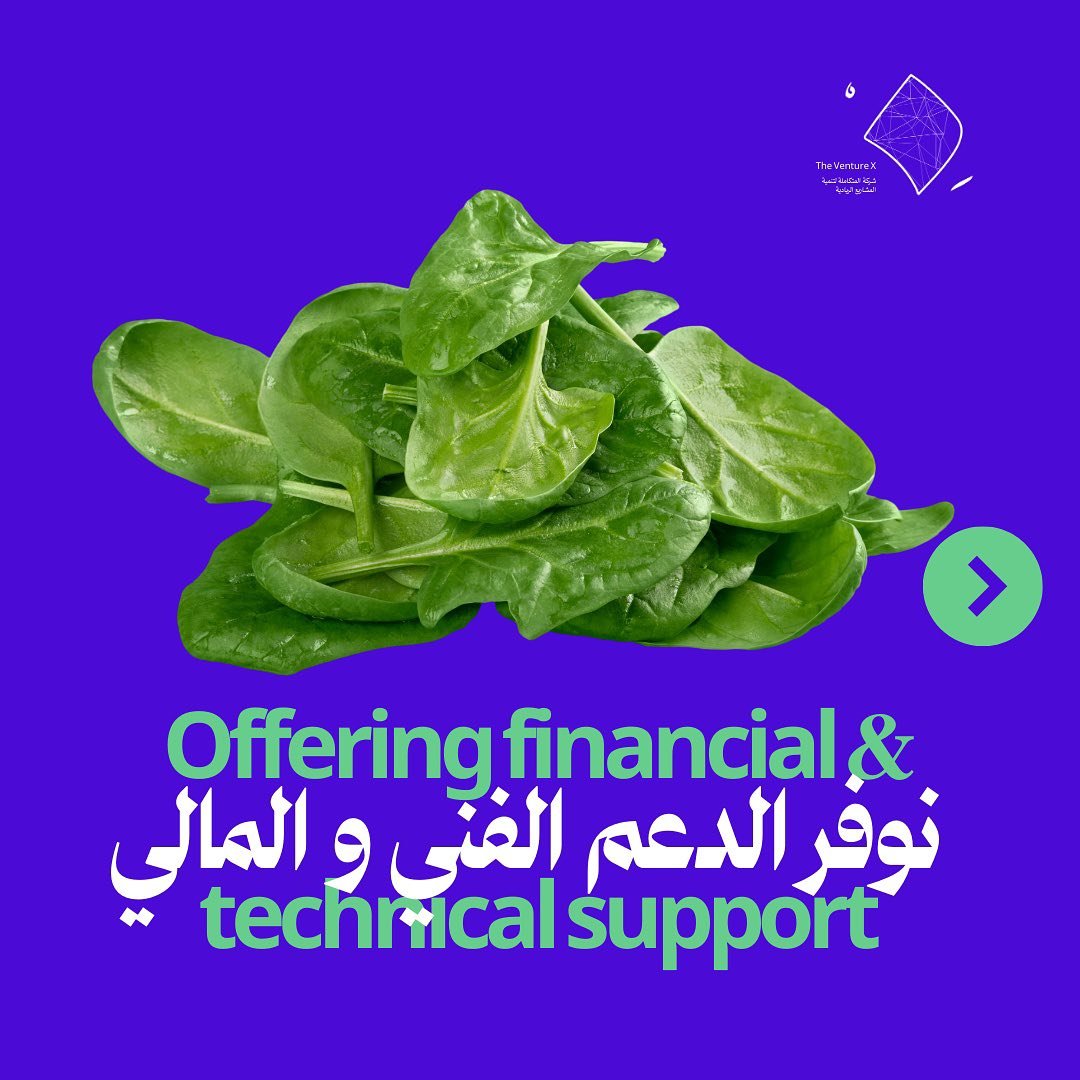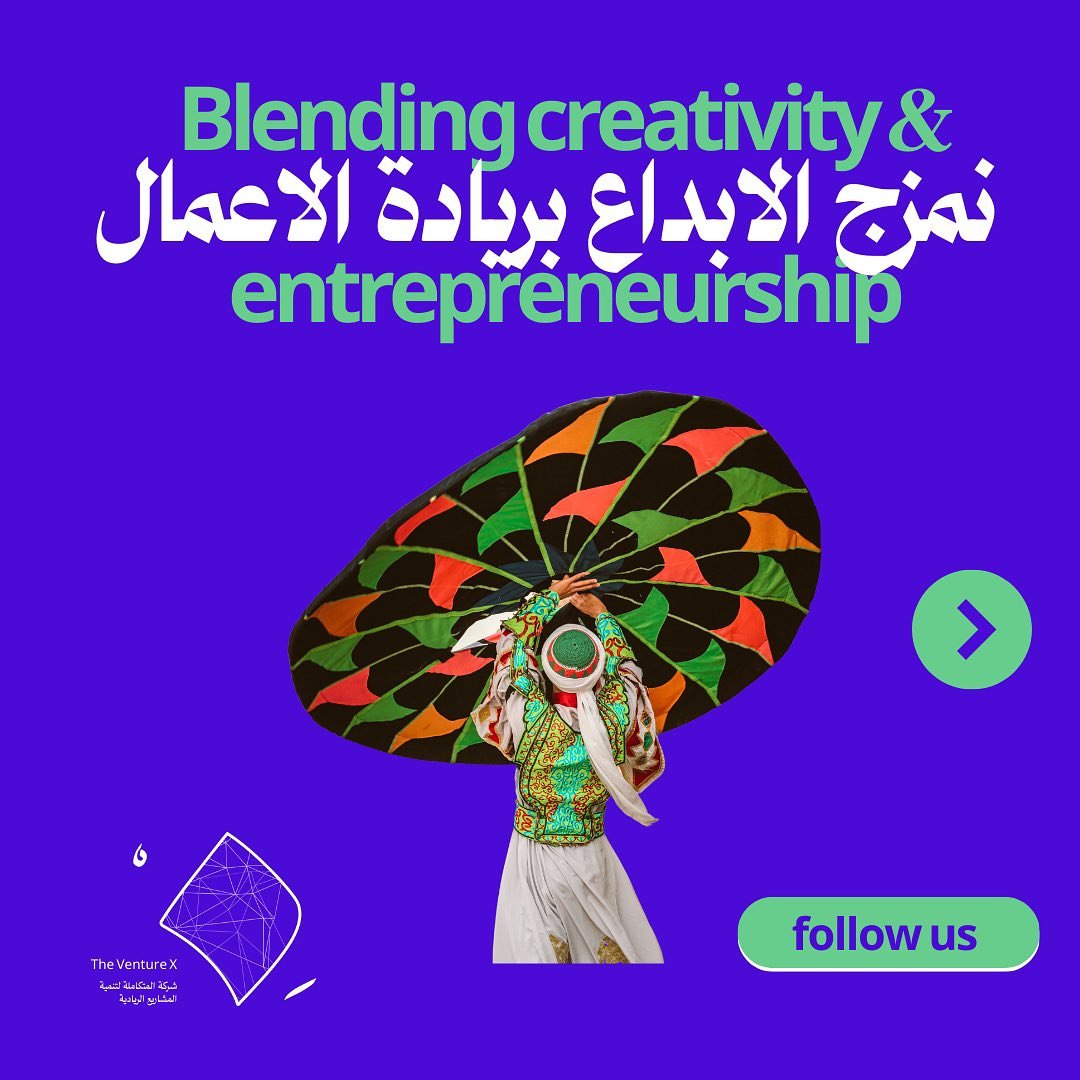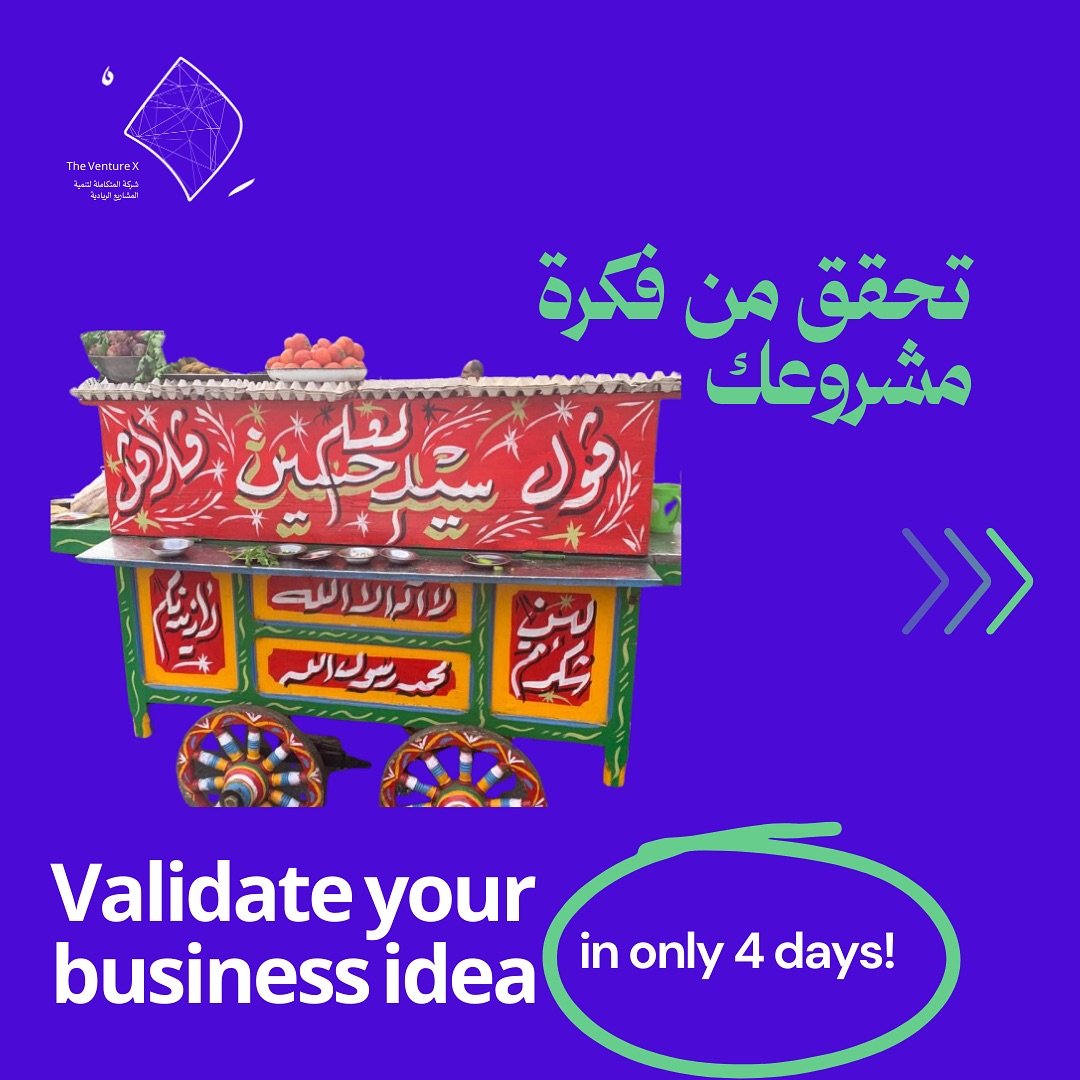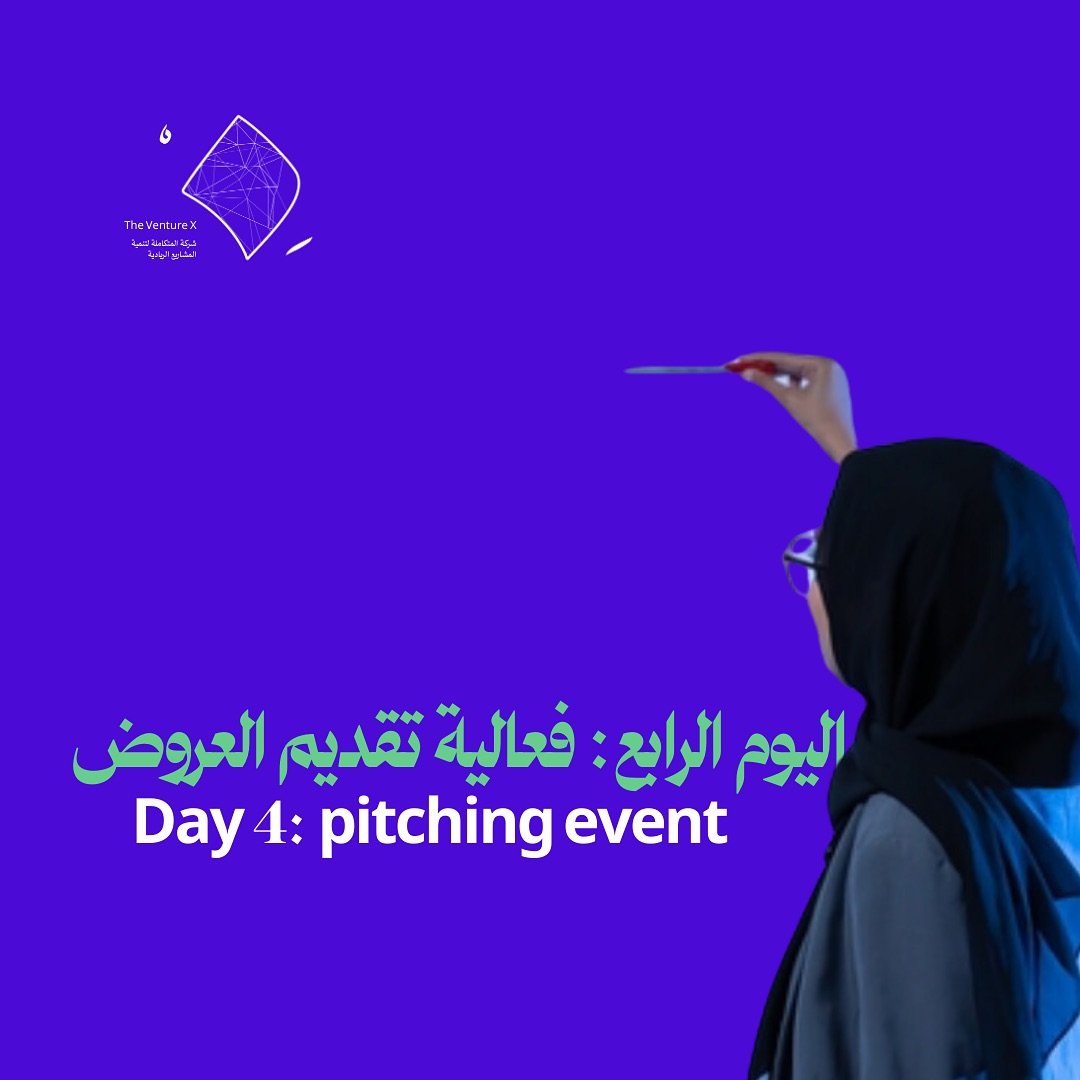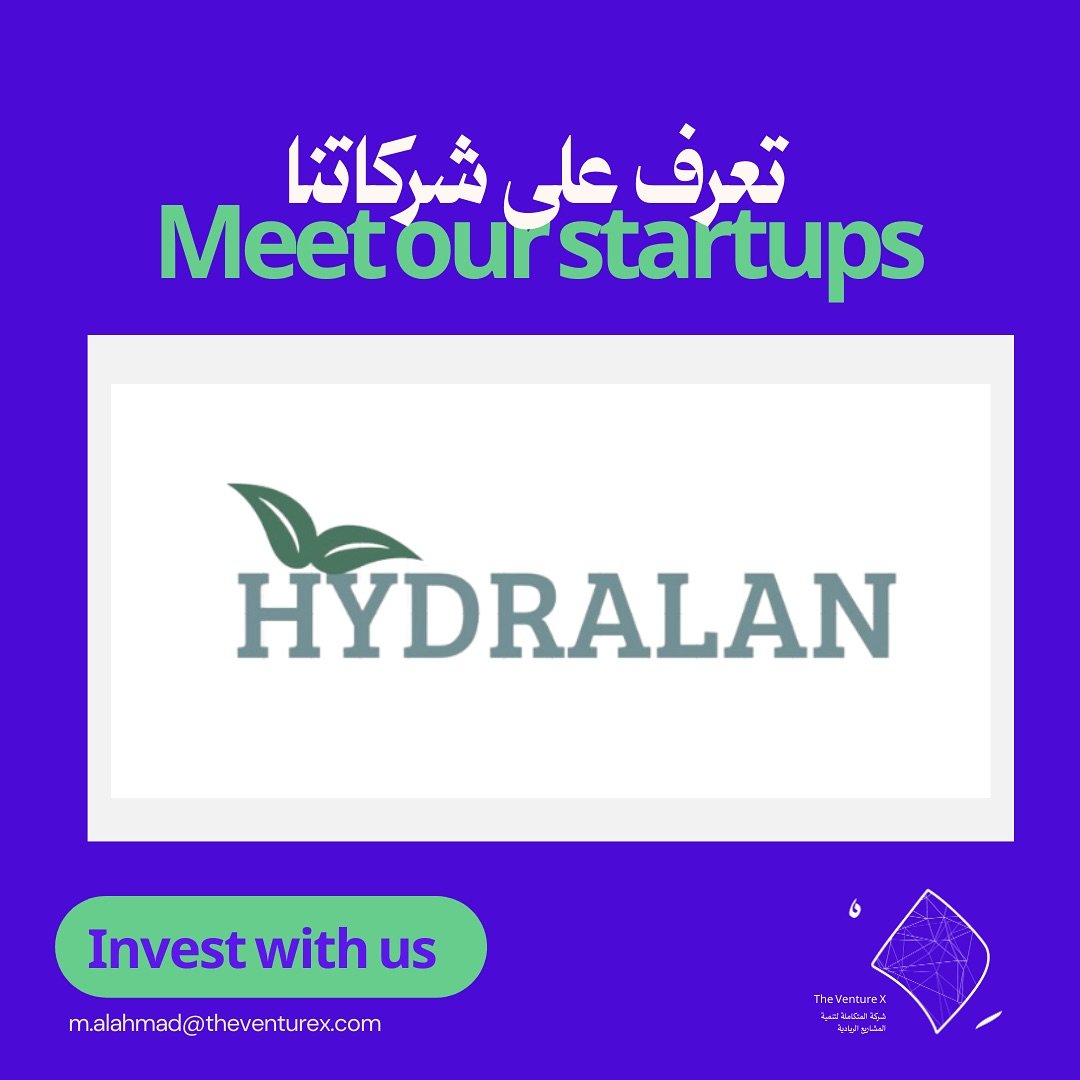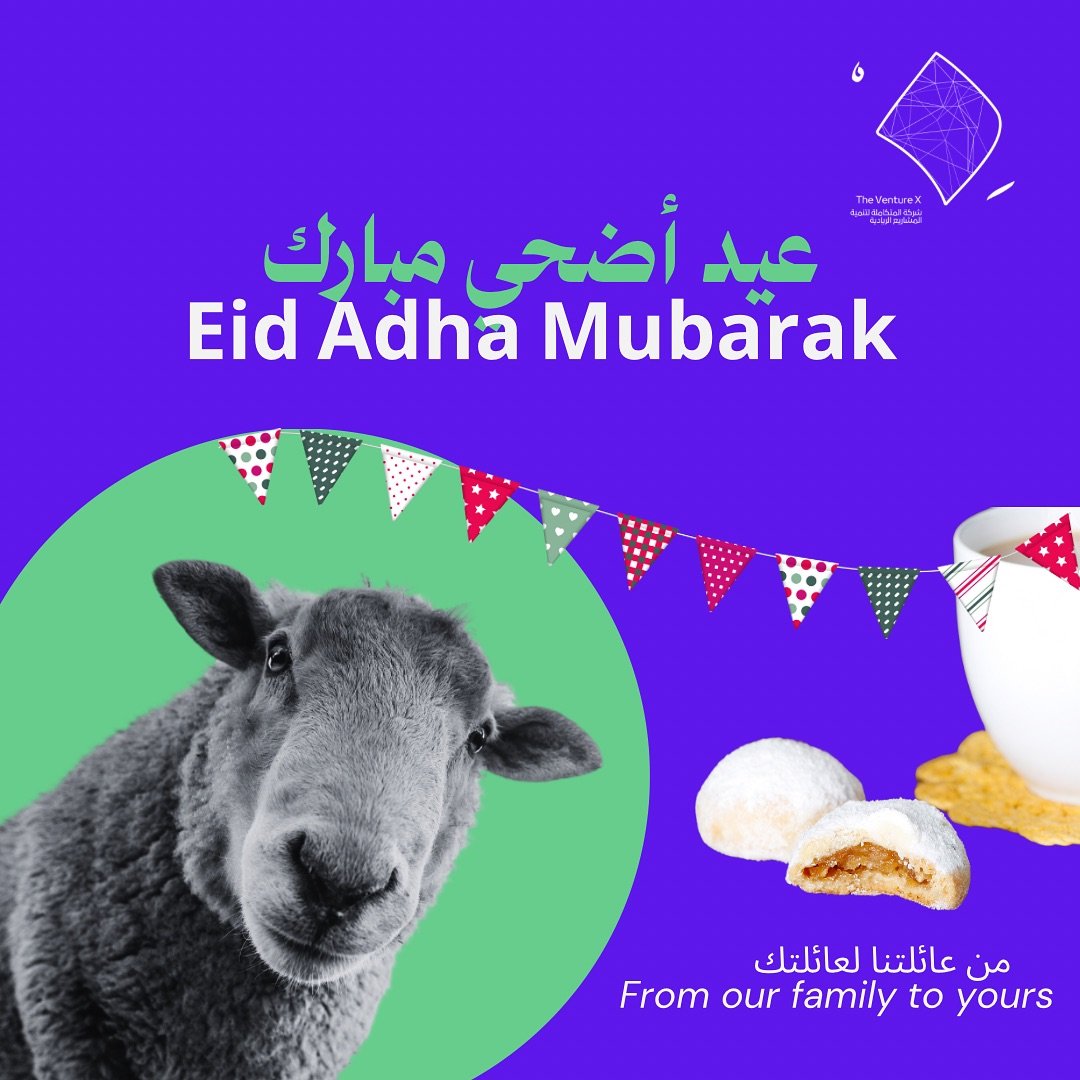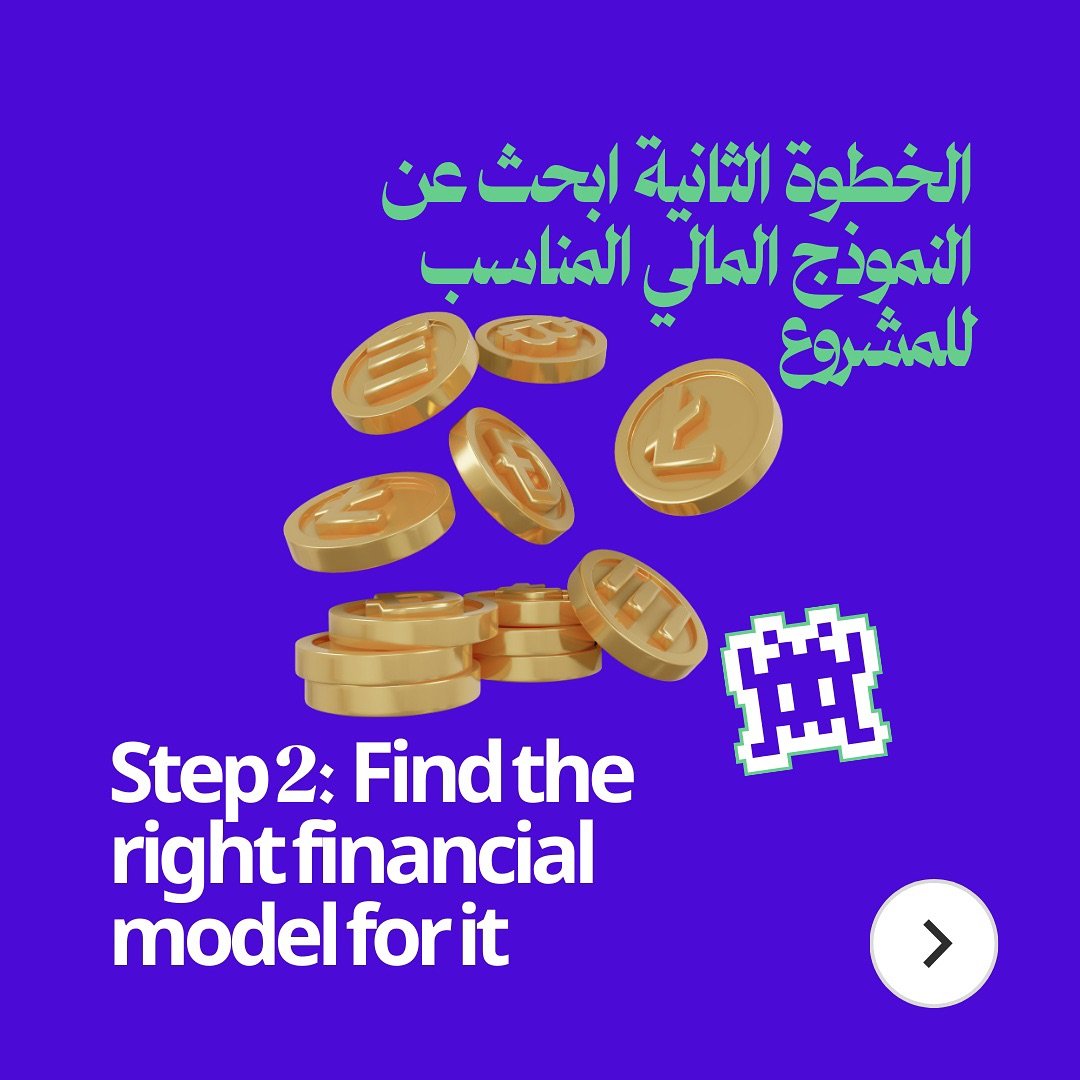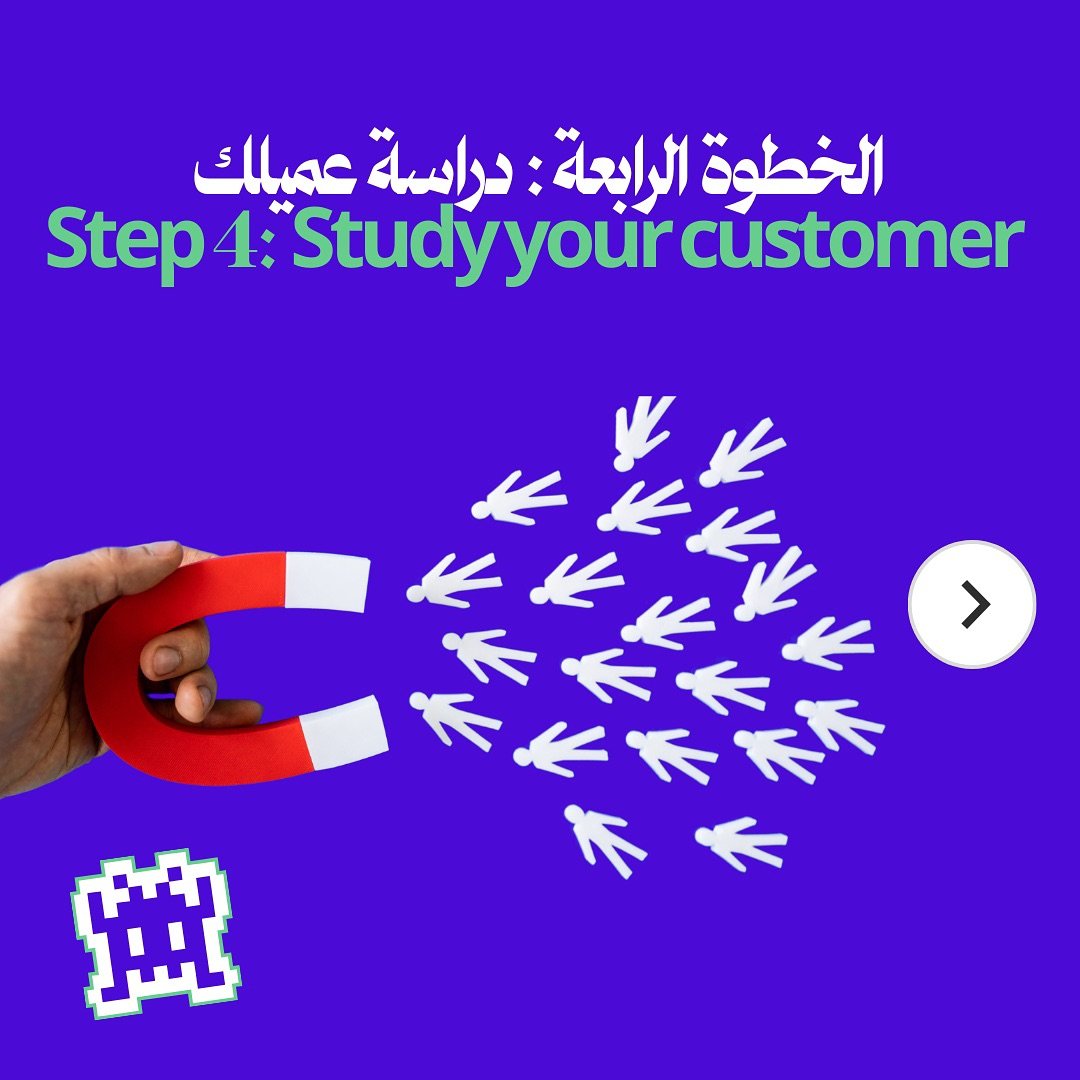
استخدام خط رواسي للعناوين – VentureX
رواسي للعناوين هو خط طباعي يجمع بين التصميم التقليدي والحديث. بحواف حادة وتباين جذاب، يُضيف هذا الخط لمسة فاخرة وحديثة لأي تصميم. مع تفاصيله المميزة من مجموعة أوبن تايب، مثل الحروف المركبة، يُقدم لك تجربة طباعية فريدة ببساطة.